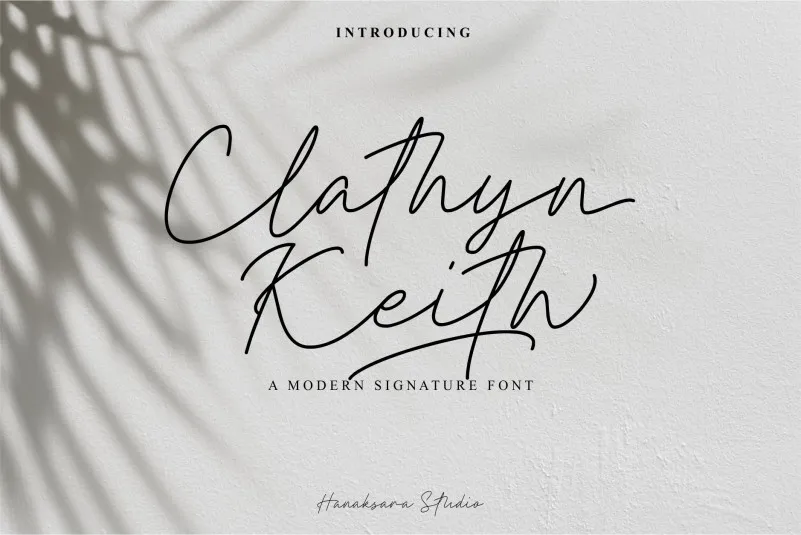
Clathyn Keith Signature Font – Fonte Grátis
Clathyn Keith Signature Font
A Clathyn Keith Signature Font é uma escrita cursiva elegante criada para marcasar seus materiais com sofisticação. Este projeto do Designer Hanaksara.Studio inclui mais de uma dúzia de ligações e várias configurações alternativas, alongadas e traços sobradosos que permitem criar estilos únicos. Seja para a identidade visual de sua marca ou para o design de um projeto gráfico, esta fonte oferece opções infinitas e personalizadas. Ideal tanto para uso pessoal quanto profissional, ela é perfeita para aqueles que buscam uma escrita única e imprimível de alta qualidade. Descubra a variedade de possibilidades criativas que essa font pode trazer ao seu design!